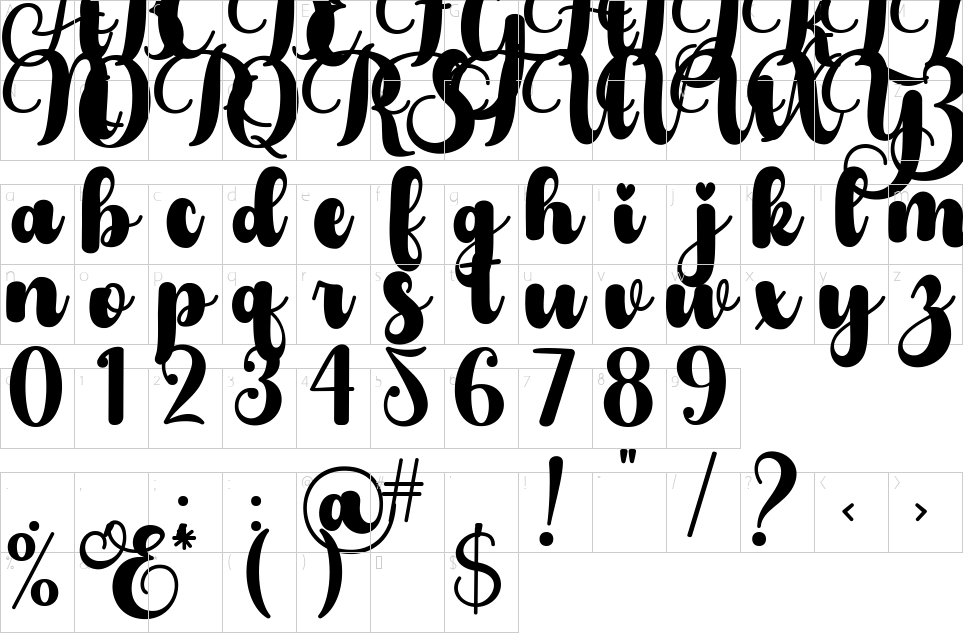
Alistia é uma elegante fonte que oferece um tom confortável e uma aparência arredondada, perfeita para escrita editorial e design de websites. Criada pelo George Studio, esta fonte foi projetada para atender aos requisitos de design gráfico e editorial, proporcionando uma escolha versátil para quem busca uma fonte moderna e minimalista. Com seu design fluido e harmonioso, Alistia é perfeita para textos de tamanho médio a grande, se destacando em um ambiente digital contemporâneo. Recentemente, a fonte já foi baixada 725 vezes, evidenciando sua popularidade crescente entre designers e produtores de conteúdo. Se você está procurando uma fonte moderna e de alta qualidade, Alistia é uma opção sólida para adicionar ao seu kit de ferramentas de design.